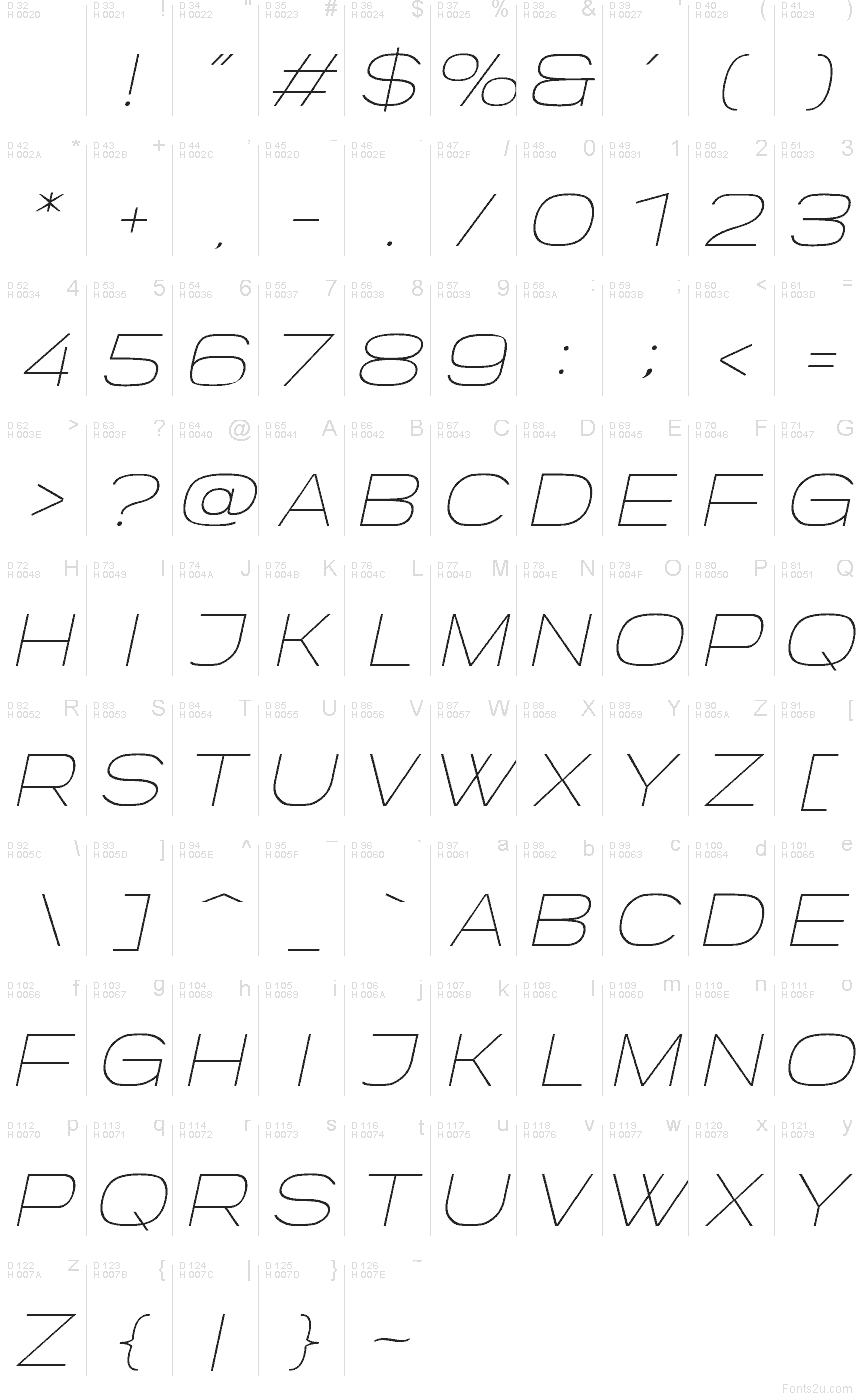
Borndia Light Italic di Muhamad Fikry Nuralif di Fikryal Studio è un font sans serif gratuito; il taglio di questa famiglia Borndia sembra disegnato con il tratto di una penna dalla punta finissima. L'inclinazione accentuata e i contatori aperti le conferiscono un ritmo elegante e aerodinamico: è pulito, arioso e veloce, senza mai risultare gridato. Si legge come metallo levigato o filo d'acciaio, specialmente nei corpi grandi.
Con Borndia Light Italic otterrai risultati nitidi per branding di moda, titoli editoriali, loghi moderni, poster, packaging, banner social e testi in evidenza su landing page tecnologiche. Questo font gratuito eccelle anche nella segnaletica minimalista, dove lo spazio e la leggerezza sono fondamentali. Abbinalo a un sans serif neutro più robusto per il testo principale, oppure affiancalo a un peso regular di Borndia per creare subito una gerarchia visiva.